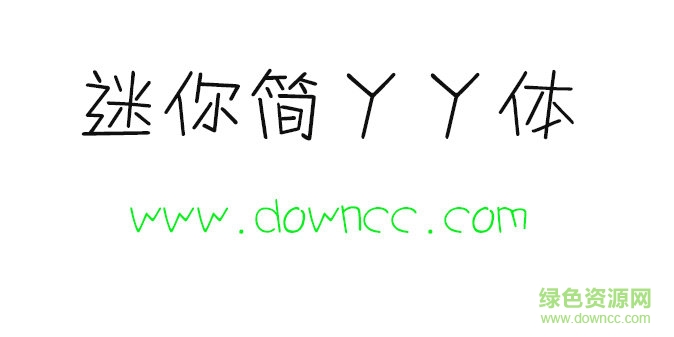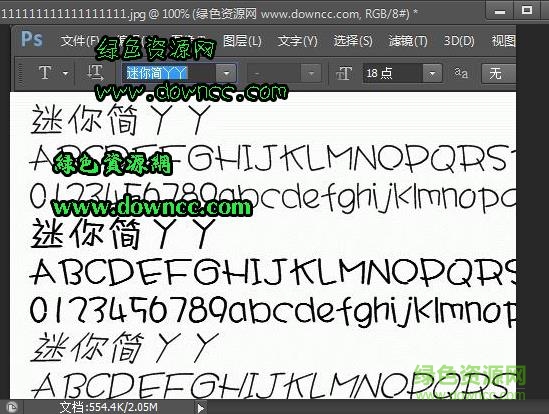
迷你簡(jiǎn)丫丫體
迷你簡(jiǎn)丫丫體是一款能夠讓你感覺(jué)到字體運(yùn)動(dòng)起來(lái)的有趣字體樣式,為你讓你能夠運(yùn)用到比較活潑的編輯工作當(dāng)中,如進(jìn)行繪畫(huà)制作與動(dòng)漫制作或者視頻字幕當(dāng)中都能夠?qū)崿F(xiàn)非常不錯(cuò)的效果!
迷你簡(jiǎn)丫丫體為你帶來(lái)了有趣的字體風(fēng)格樣式,同時(shí)能夠隨意為其添加眾多藝術(shù)效果!